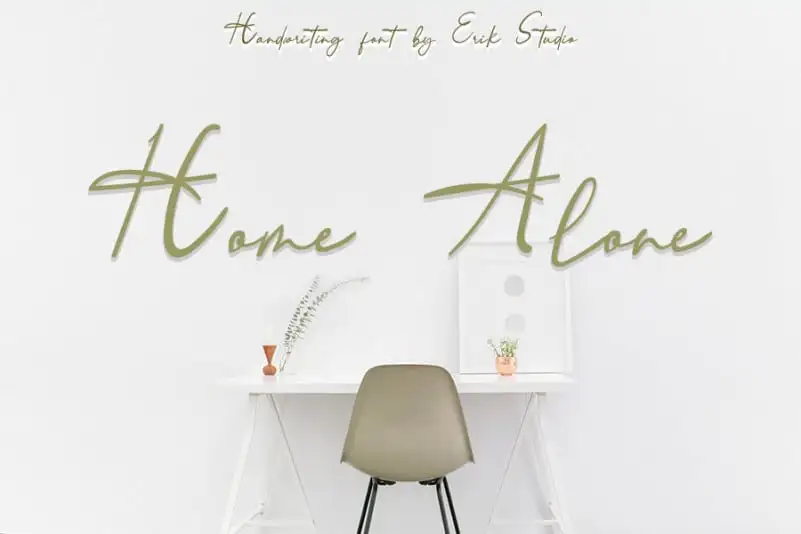
Home Alone Script Font – Fonte Grátis
Home Alone Script Font
A fonte ‘Home Alone Script Font’ é uma elegante tipografia de desenho à mão com letras que dançam pelo piso base. Suas formas são delicadas e alegres, tornando-a perfeita para escrita de convites de casamento, cartões ou qualquer outro design que possa precisar um toque romântico e pessoal. Esta fonte é ideal para aqueles que querem dar um brilho especial à sua arte digital. É uma escolha ótima para designers apaixonados por criar mensagens únicas e memoráveis, seja para presentes de casamento exuberantes ou simples cartões natalinos com toques românticos. Com a ‘Home Alone Script Font’, os criadores podem se destacar no design digital, adicionando um ar de romantismo que torna as criações mais autênticas e emocionantes. É uma fonte perfeita para quem busca expressar sentimentos através do uso da letra, seja numa mensagem sincera ou num design memorável. Torna-se a escolha ideal para designers aficionados em criar experiências de visualização memoráveis com um toque único. Sua natureza romântica e delicada torna-a uma fonte perfeita para qualquer projeto que possa ganhar vida através da palavra escrita.